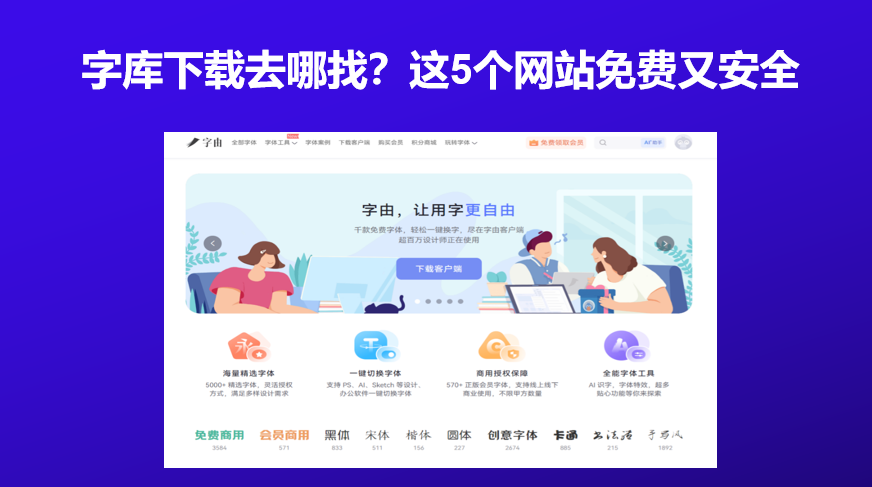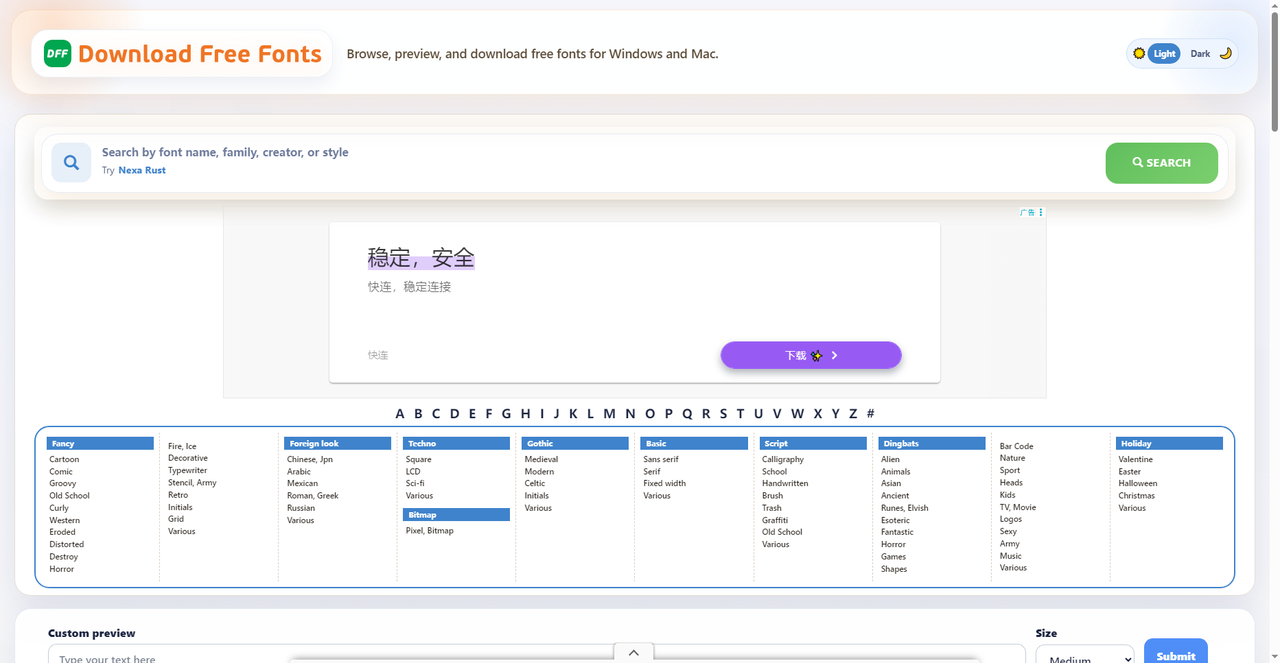
字库下载去哪找?这5个网站免费又安全
做设计的时间久了就会发现手头里的素材根本就不够用,每次遇到新的设计情况总会现去找素材,但是这时候会发现有些网站下载素材会捆绑一些垃圾文件,又或者是碰到下载的软件没有写明版权等等问题,其实字库下载这件事,关键不是你找到多少款字体,而是你从哪下、怎么确认授权。今天整理的这5 个网站,每个都在授权清晰度和下载安全性上做得比较到位,可以放心使用。
先聊字由,它和传统字体下载站最大的区别是:你不需要下载任何字体文件。字由的客户端里收录了上万款字体,其中免费商用超过3500款。你在客户端里找到想要的字体,点一下“激活”,字体会自动出现在PS、AI、Word的字体列表里,不用去C盘翻文件夹,也不用重启软件。
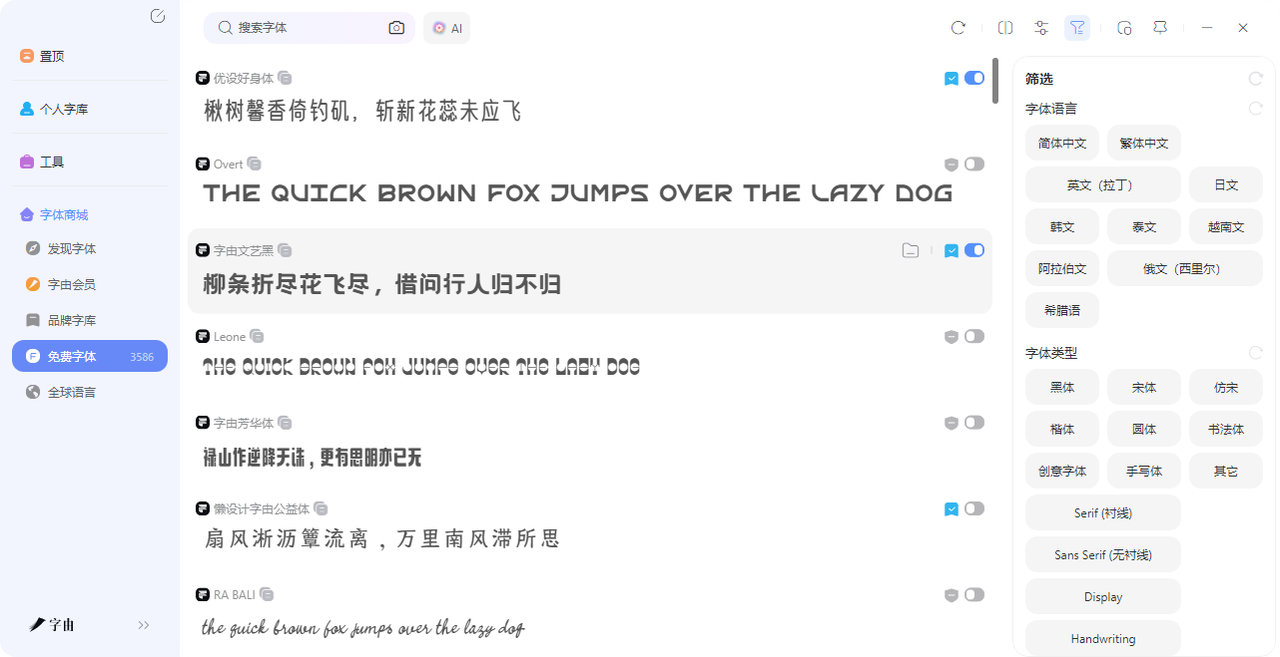
字由的筛选功能很实用:按“免费商用”筛选,出来的全是能放心用在商业项目里的字体;按“手写体”“书法体”筛选,做签名或标题时很快能找到方向。如果你在多台设备上工作,字由的云字库可以把收藏的字体同步到所有电脑,不用每台都重新下载。
字由还有AI字体功能,输入文案就能直接生成艺术字图片,适合那些连字体都懒得选、只想快速出图的场景。总的来说,字由是一个“字库管理+AI生成”的综合平台,如果你经常换字体、怕版权问题、不想折腾安装步骤,字由比传统下载站省心很多。
2、Download Free Fonts
第二个网站叫Download Free Fonts。它提供按字体名称、设计师、风格搜索的功能,首页展示了最近添加的新字体,比如JHC Audemars、Kunaroh、Neco等。这个站的特色是“新”。很多字体下载站更新慢,但这个站经常有新字体上架。每款字体都标注了分类(Serif、Various、Sci-fi等),下载前可以预览效果——在“Custom preview”框里输入你自己的文字,实时看渲染效果。需要注意的是,这个站上的字体授权类型比较混合,下载页面会标注是免费商用还是个人使用,建议下载前看一眼。如果你想找一些比较新、比较小众的英文字体,这个站值得翻一翻。批量下载时注意授权一致性。有些网站允许你一次性把整包字体都下载下来,但包里面的字体可能混合了免费商用、个人使用、甚至需要付费的。不要一股脑全装进电脑,否则哪天商用的时候可能会不小心用错。可以在下载前先看一眼网站是否提供了“仅免费商用”的筛选功能,或者在下载后逐个确认授权。
3、Free & Premium Fonts
第三个网站叫Free & Premium Fonts。它的界面简洁,左侧有字体列表,右侧是大尺寸预览区。你可以调整预览文字的字号(24pt、36pt、48pt、72pt),实时看到不同尺寸下的显示效果。这个站同时收录免费字体和付费字体,免费的有Core Struct、Silver Flux等,付费的会有Premium标记。如果你预算有限,可以直接筛选免费版。预览功能是它最大的优点——很多字体下载站只给一张小图,但这里你可以输入自己的文案,调大字号,仔细看笔画细节,再决定要不要下载。
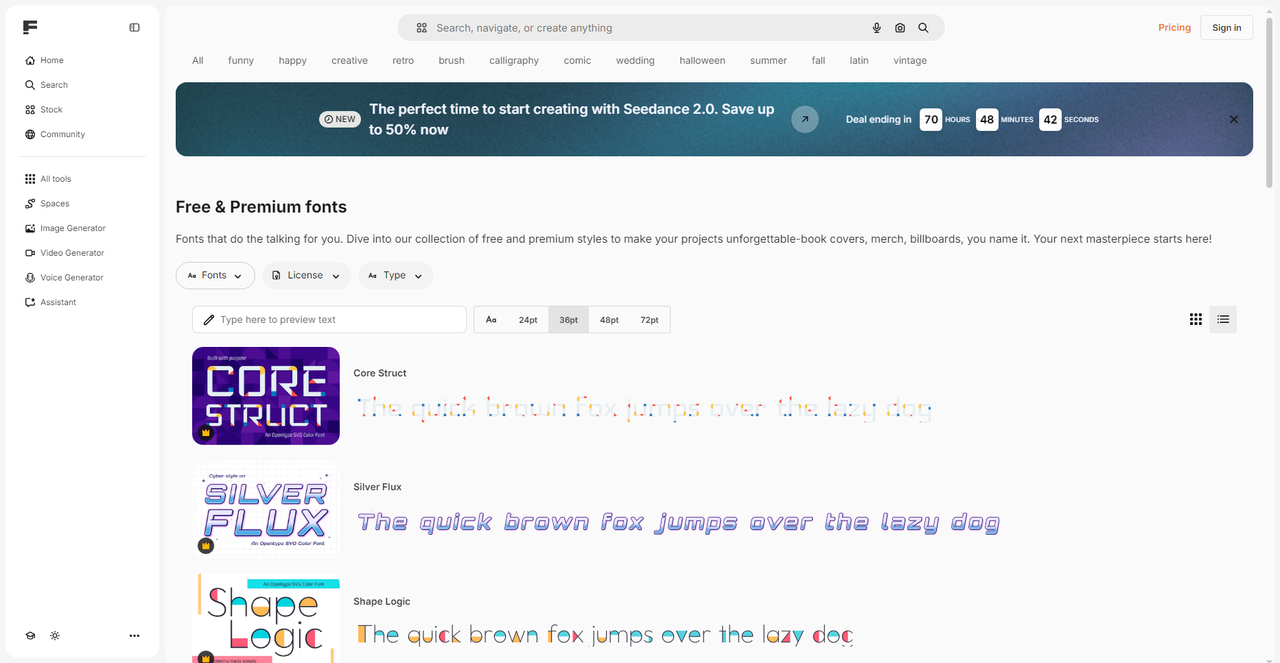
4、FREE FONTS
第四个网站就叫FREE FONTS。它最大的卖点是数量——首页写着8,400 Free Downloadable Fonts。分类细致到令人发指:Fancy、Basic、Script、Display、Misc、Dingbats、Premium,点开“Fancy”还有Comic、Cartoon、Decorative、Retro、Stencil、Fire-Ice等子分类。每款字体都有预览图和下载按钮。授权方面,免费区的基本都是免费使用,但商用建议点进详情页确认。如果你经常需要按风格找字体,或者喜欢像逛超市一样翻分类,FREE FONTS的体验比那些只有一个搜索框的网站好很多。
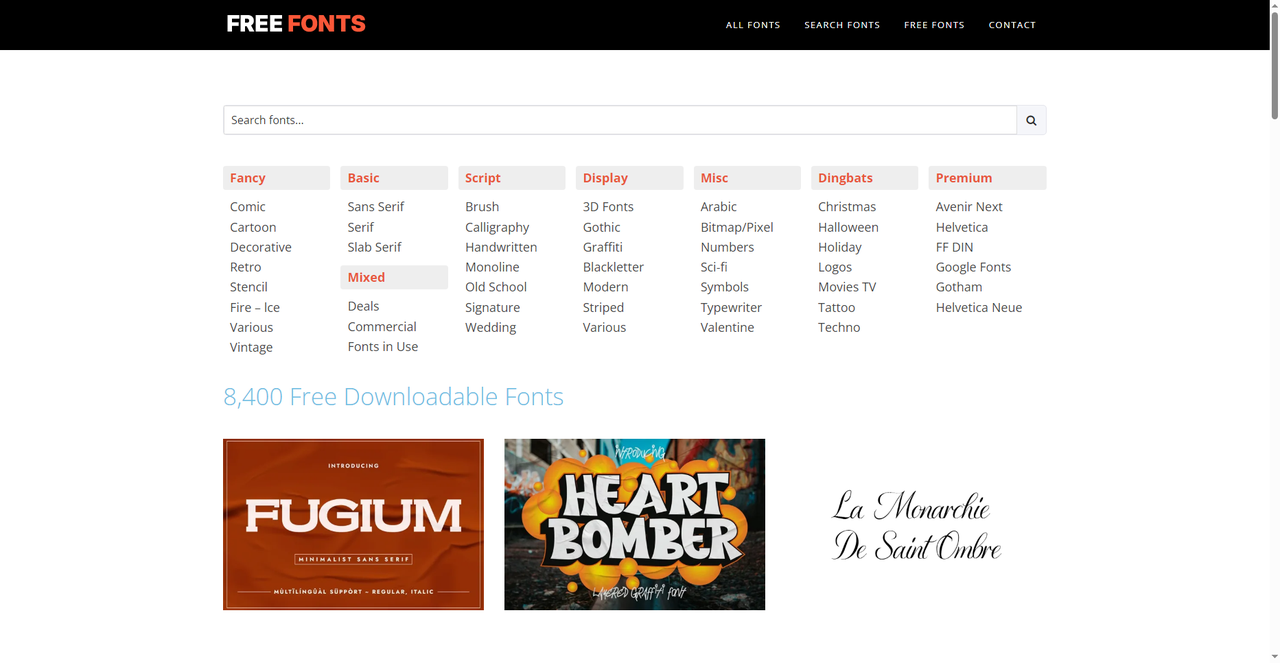
5、Fontshare
第五个网站是Fontshare,由印度字体公司Indian Type Foundry运营。它不是一个杂乱无章的字体聚合站,而是一个精选的高品质免费字体库。Fontshare上的每款字体都是专业字体设计师作品,质量明显高于一般免费字体站。比如截图里的Satoshi,是一款几何无衬线体,提供了10种字重和可变字体版本,设计考究,适合品牌和UI设计。Fontshare的授权非常友好:所有字体免费用于个人和商业项目,不需要署名,不需要注册就能下载。它还提供“字体配对”功能,帮你推荐哪些字体搭配在一起好看。如果你受够了那些粗糙的免费字体,想要专业级别的免费字体,Fontshare是非常值得收藏的网站。
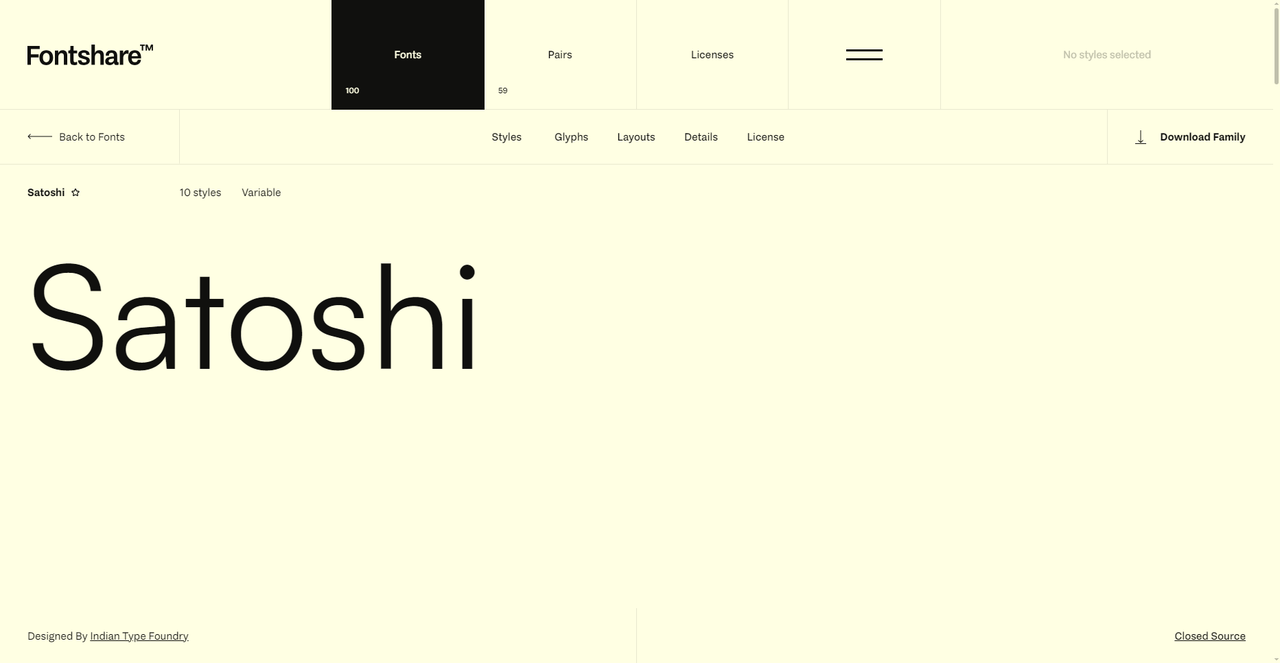
选字体下载站,核心就两条:授权清不清晰,下载安不安全。字由不用下载文件、一键激活,授权标注清楚,适合怕麻烦的用户;Download Free Fonts新字体更新快,适合追新的设计师;Free & Premium Fonts预览功能强,适合精细对比;FREE FONTS分类变态细,适合按风格翻找;Fontshare品质最高,适合对字体质量有要求的专业项目。如果这里面有你感兴趣的就可以先收藏然后码住!下次用到的时候不迷路。